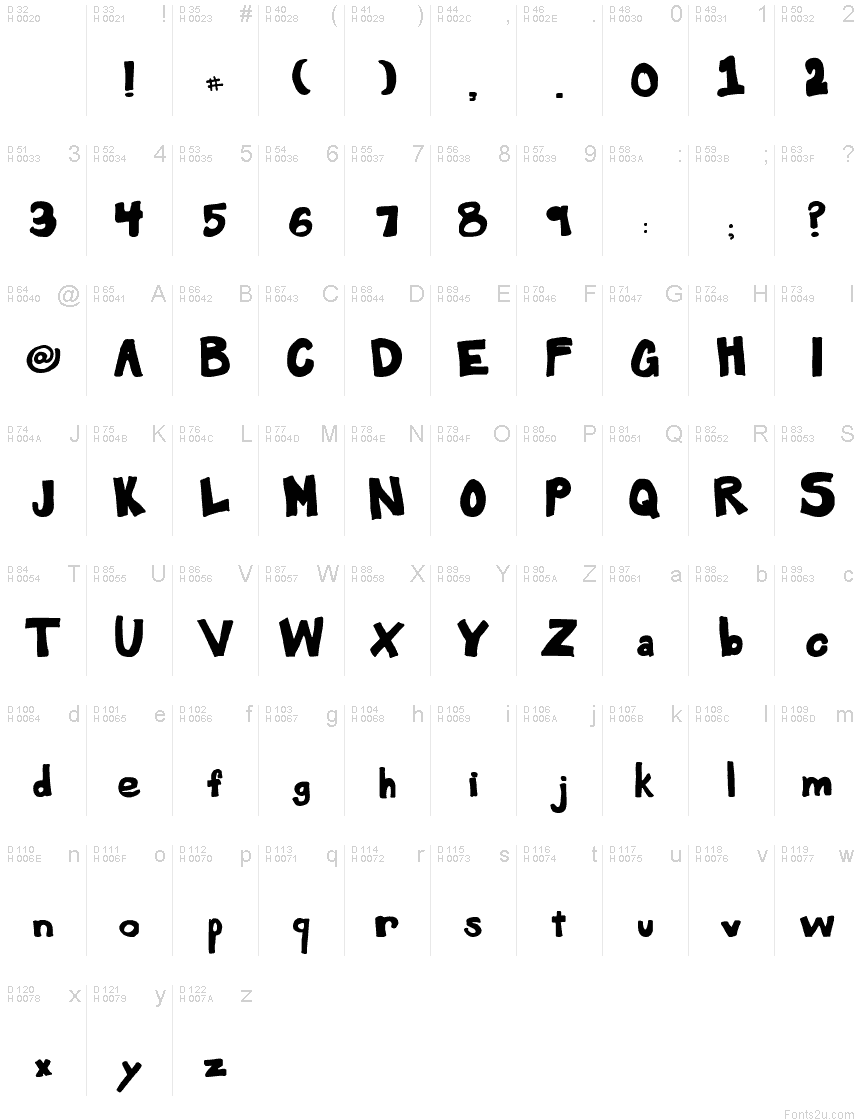
Yard Sale Regular 字体
Yard Sale Regular
Fonts-A-Go-Go
Jennifer Heinicke
Yard Sale 是由 Fonts A Go-Go 的 Jennifer Heinicke 设计的一款免费卡通风格标题字体,它带着一种类似跳蚤市场手绘招牌般随性且略显粗犷的魅力。字母采用了厚重、不规则的轮廓和柔和圆润的曲线,让整款字体透出一种居家、跳跃的休闲感,相比起精致的商业字体,它更具手工打造的质朴趣味。
这种非主流的格调非常适合海报标题、跳蚤市场设计、儿童活动传单、小志(zine)封面以及各类商店招牌,能为你营造出友好且带点粗粝的复古感。作为一款免费字体,它在标题卡和短标语中使用效果极佳,因为其宽大而奇特的字形本身就充满个性,无需过多文字修饰即可脱颖而出。